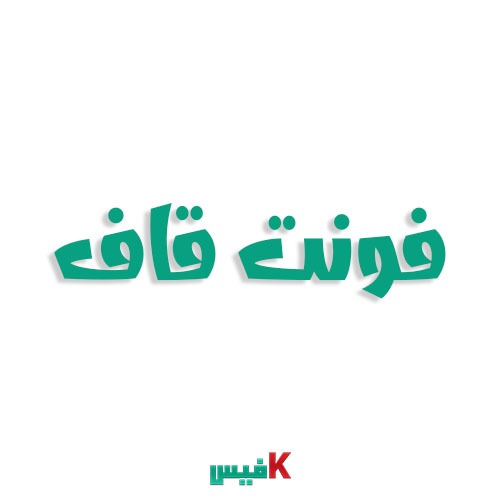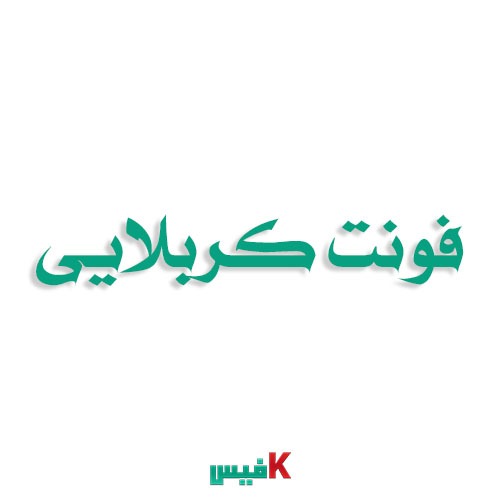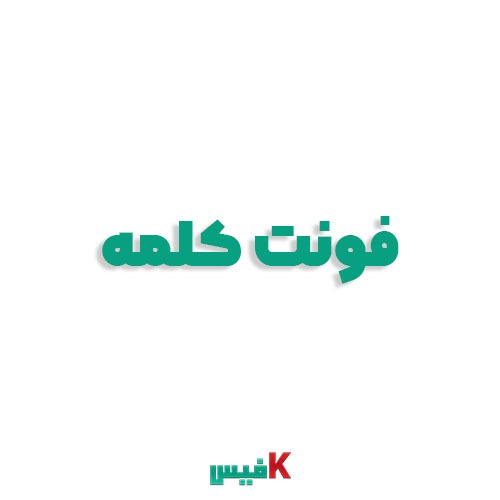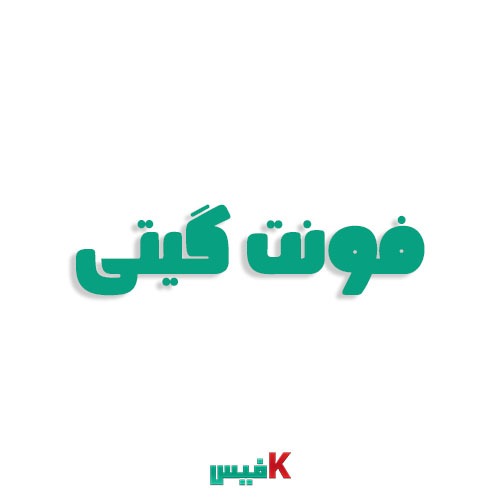
فونت قاف فارسی (رایگان)
ویژگی های فونت:
• کیفیت بالای طراحی
• اعداد و حروف انگلیسی متناسب با فونت
فونت کربلایی عربی فارسی (رایگان)
• فونت مذهبی مناسب طرح های گرافیکی
• فونت تک وزن و شامل یک ساختار
• مناسب استفاده برای متن های طولانی
• مناسب طرح های مذهبی و عاشورایی
فونت کلمه فارسی
یکی از ویژگی های برجسته کلمه، پشتیبانی از زبان های فارسی، عربی و انگلیسی است که آن را به انتخابی مناسب برای پروژه های چندزبانه تبدیل می کند. همچنین، این فونت از زبان های اردو و کردی نیز پشتیبانی می کند که دامنه کاربرد آن را گسترده تر می سازد.
فونت گفته فارسی
فونت گفته فریاد جسورانه دنیای تایپوگرافی فارسی
فونت گفته، همانند اسمش، حرف‌های زیادی برای گفتن دارد. این فونت از دنیای خط و ‌نوشت بیرون زده و بر بوم طراحی گرافیک، فریاد جسورانه ای از هنر، شخصیت و متمایز بودن را سر داده است. در این دنیای دیجیتالی مملو از فونت‌های یکنواخت، گفته با ساختار هندسی منحصربه‌فرد و روحیه هنری پررنگش، توجه هر بیننده‌ای را به خود جلب می‌کند.
فونت گیتی فارسی
فونت گیتی فونتی با کاربرد نمایشی است طراحی ابتدایی این فونت با استفاده از ماژیک و به صورت آزادانه ،بدون در نظر گرفتن اصول طراحی و به صورت بداهه انجام شد و سپس با ویرایش ها و اصلاحات متعدد و اضافه کردن حروف ترکیبی و جایگزین سعی شد حروف به صورت کاربردی طراحی شوند و در اختیار کاربران قرار بگیرد.
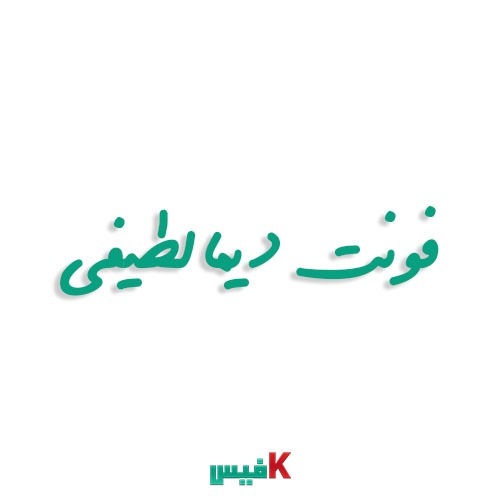
فونت لطیفی فارسی (رایگان)